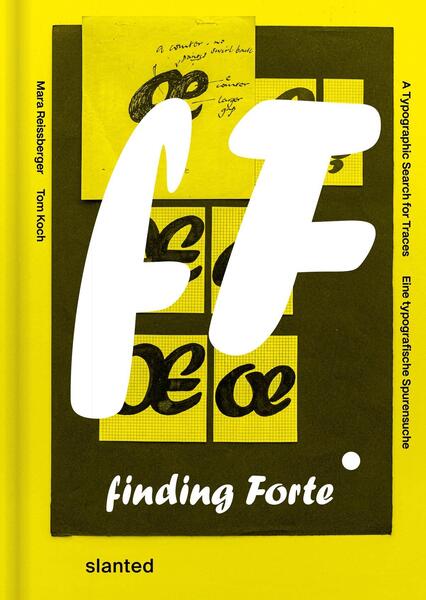
Forte, diese lebendige und freundliche Schrift, die jeder kennt, wird seit über sechs Jahrzehnten verwendet, missbraucht und überstrapaziert, seit sie 1962 von der Monotype Corporation veröffentlicht wurde. Bekannte Persönlichkeiten aus der Welt der Typografie wie Stanley Morison und Vincent Connare standen im Rampenlicht der lebhaften Lebenslinien dieser Schrift. Aber der Designer der Schrift, Karl Reißberger, blieb wenig bekannt. Bis jetzt.
Dieses Buch begibt sich auf die Suche nach »Fundstücken« wie Reißbergers frühen Plakaten, Originalentwürfen und Werbematerialien, um die Entstehungsgeschichte der »Schrift, die jeder kennt« nachzuzeichnen. Sechzig Jahre nach dem ersten Erscheinen der Forte hat sie als Toshi Omagaris überarbeitete Schrift, Forte Forward, neues Leben gefunden. Sie erscheint zusammen mit diesem Buch.
Auch die künstlerischen Visionen von einunddreißig zeitgenössischen Künstlern, die sich mit der Formensprache der Forte im Dialog mit ihren historischen Umrissen auseinandergesetzt haben, finden ihren Weg in dieses Buch. Die Interpretationen dieser internationalen Kreativen eröffnen neue Zugänge zur Typografie.
Finding Forte – Eine typografische Spurensuche